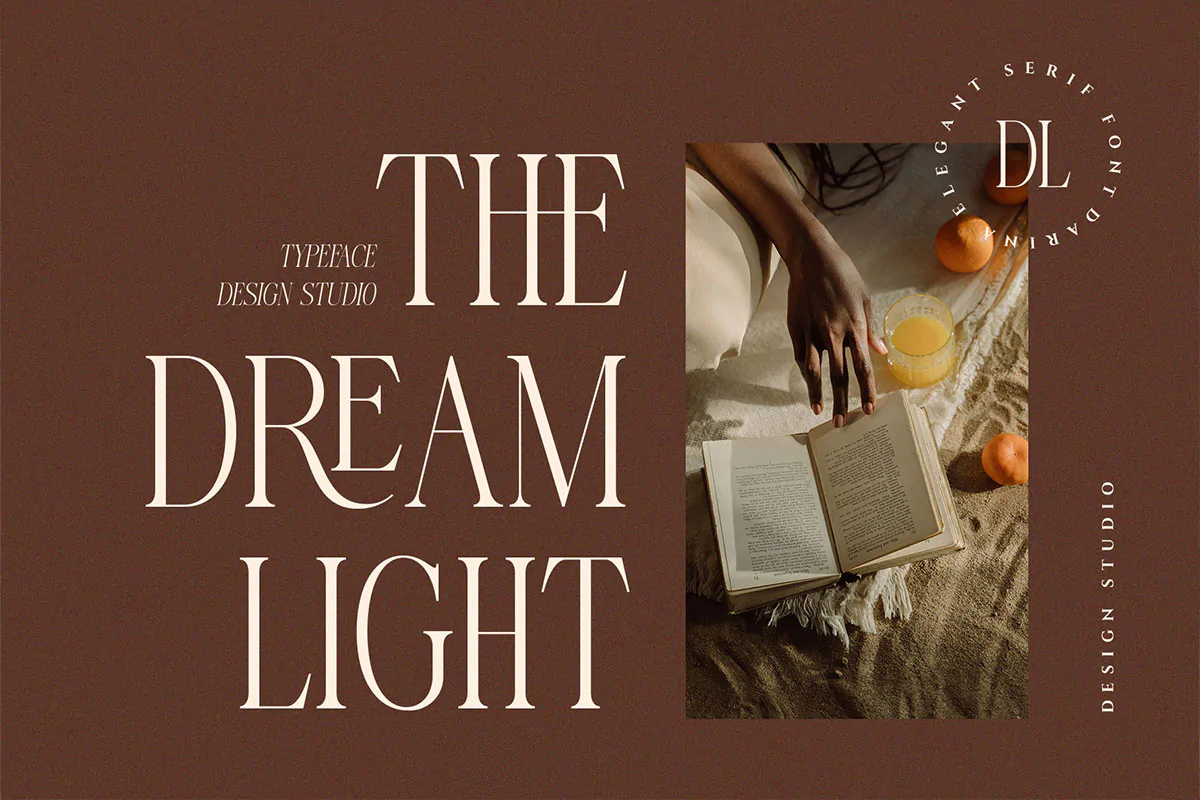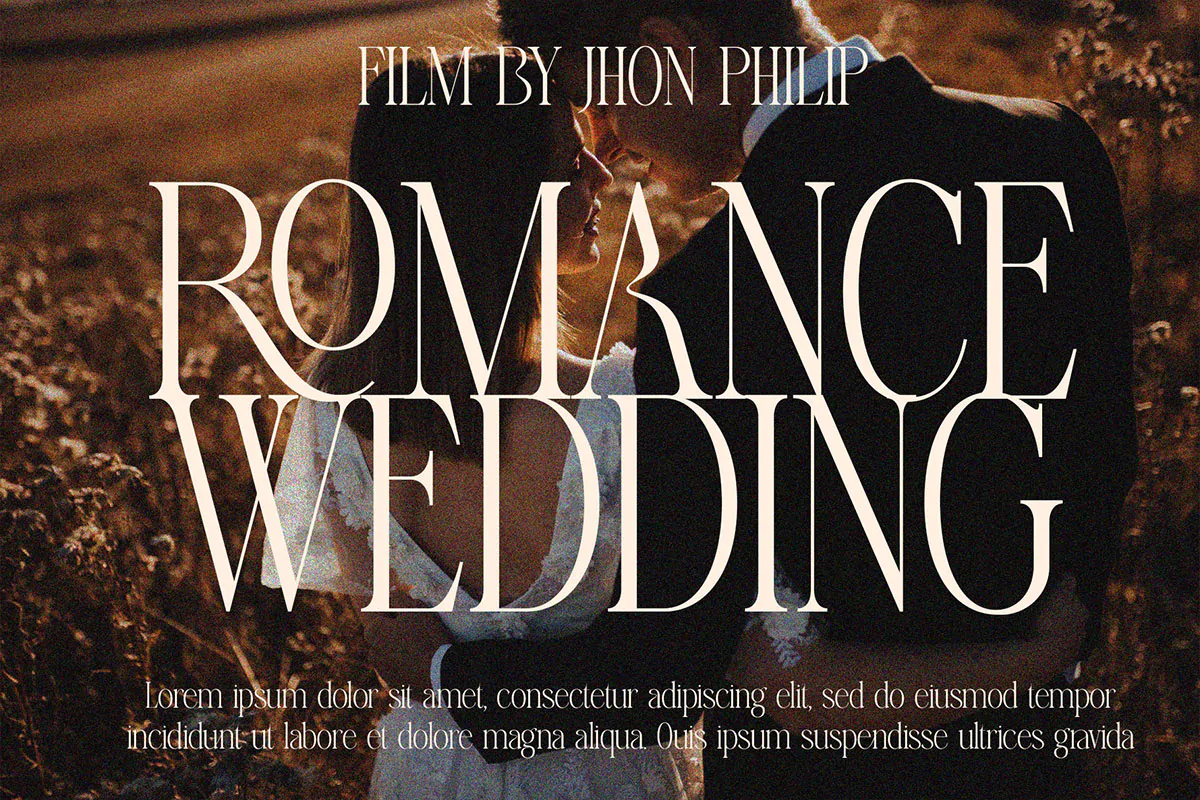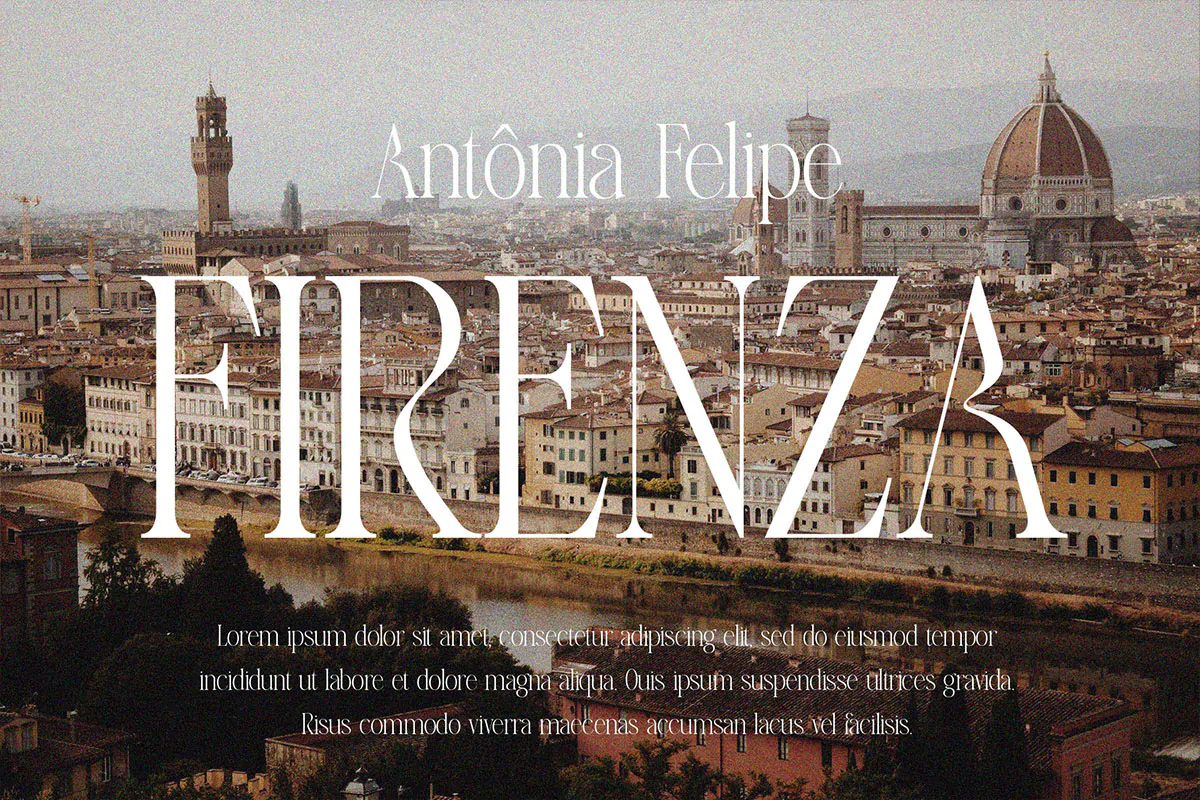
فونت انگلیسی مدرن Darina
فونت انگلیسی مدرن
فونت انگلیسی مدرن Darina یک اسکریپت فونت فوق العاده زیبا است که میتوان از آن در طرح و پروژههای مختلف همچون طراحی پوستر، بنر، کارت ویزیت، بروشور، بسته بندی محصولات، آرایشی و بهداشتی و دیگر پروژههای گرافیکی استفاده نمود.